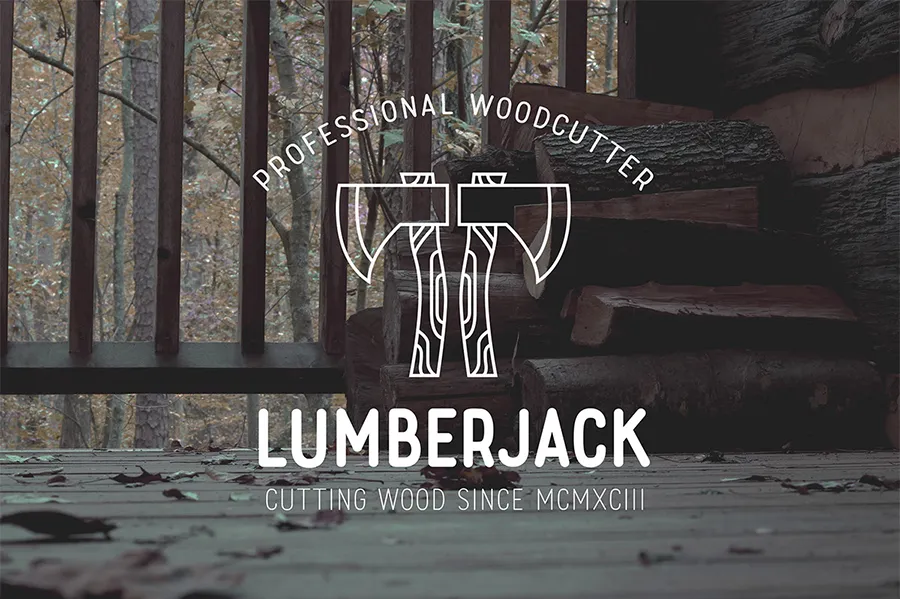
A Rolade Typeface é uma fonte tipográfica sans serif que destaca-se pela sua consistência no tamanho dos caracteres. Esta opção elegante para aplicações visuais, como logomarcas, selos e títulos, oferece um design minimalista e alegre. Inspirada em estilos de antigos exemplares, esta fonte é projetada com proporções compactadas que permitem uma leitura eficiente mesmo sob condições de iluminação mais fraca. Perfeita para designers que desejam dar destaque visual sem se preocupar com detalhes complexos, a Rolade Typeface oferece um estilo distintivo e moderno. Ideal tanto para criações de alta qualidade quanto para aplicações simples, ela é uma escolha perfeita para quem busca um design minimalista e elegante que ressalta o conteúdo da sua obra.